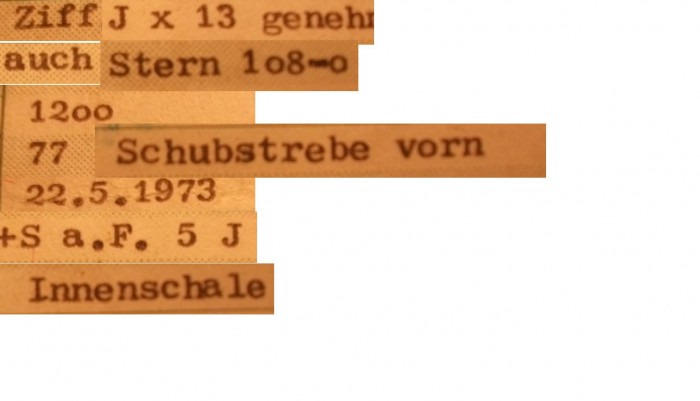
welche schreibmaschinenschrift
brauche dringend hilfe!
suche diese schreibmaschinenschrift bzw. eine schreibmaschine die genau diese schrift schreibt. weiß jemand rat und/oder kann helfen ?? habe schon diverse stunden am pc verbracht um danach zu suchen - leider total erfolglos.
mir wäre sehr geholfen wenn mir einer von euch fachleuten sagen könnte, welche maschine diese schrift schreibt.
als sehr markant habe ich die zahl 2 feststellen können , da diese im unteren bereich diese von mir bis dato noch nicht gefundene leichte welle nach unten hat . ebenso die zahl 5 , die im oberstrich sowie im bauch fetter sind . euch profis werden bestimmt noch andere einzelheiten auffallen .
da das schriftstück aus den 70ern stammt wird es wahrscheinlich eh schwer werden diese maschine zu finden. willst du etwas nachtippen oder reicht dir nur die info? eventuell direkt mal nach sammlern von alten schreibmaschinen suchen, die können dir vielleicht eher weiterhelfen.
Und die schiefe F und I Serifen könnten das Ergebnis eines Typenhebel-Salats gewesen sein, sodass die Typoe dann hart an einer Stelle aufgedotzt ist, wo sie nicht hingehört. Allgemein wirkt das hoppelnde Schriftbild ohnehin nach einer wschon etwas klapperigen Maschine. An solchen Eigenheiten hat man früher Erpresserbriefe einer bestimmten Maschine zugeordnet.
Übrigens hatten diese Leute auch Schriftmusterbücher aller gängigen Schreibmaschinen-Hersteller, sortiert dann nach den generischen Schriftstilen, um die unterschiede der verschiedenen Hersteller besser zu erkennen. So sah dann bei einigen Buchstaben die "Pica" der Erika (aka Universum) ein wenig anders aus, als die der Olympia oder der Adler.
BTW: Eigentlich sollte ich aus meiner Schreibmaschinen-Schrift mittels OpenType-Glyphen-Rotation mal eine mit gelockerten Typenhebeln bauen, wo die Buchstaben ein wenig herum hopsen, was mein ihr?
@robertmichael : das ist richtig , sollte so aus den siebzigern sein. ich würde gerne was nachtippen , von daher würde mir auch eine leihgabe/miete , sofern erstmal die richtige maschine gefunden ist , reichen.
@catfonts : "Übrigens hatten diese Leute auch Schriftmusterbücher aller gängigen Schreibmaschinen-Hersteller, sortiert dann nach den generischen Schriftstilen, um die unterschiede der verschiedenen Hersteller besser zu erkennen. So sah dann bei einigen Buchstaben die "Pica" der Erika (aka Universum) ein wenig anders aus, als die der Olympia oder der Adler."
wer sind "diese leute"??? wohin kann ich mich da ev. wenden ?? ich brauche ja nicht das "hoppelnde" und "klapprige" sondern eben nur die schriftart , bzw. den schreibmaschinentyp .
wenn noch jemand ideen hat - immer gerne !!
wer sind "diese leute"???
Ich glaube, Catfonts meint Kriminalbeamte, die früher gegen Erpresser ermittelt haben und sich damals noch mit schreibmaschinengetippten Erpresserbriefen herumschlagen mussten.